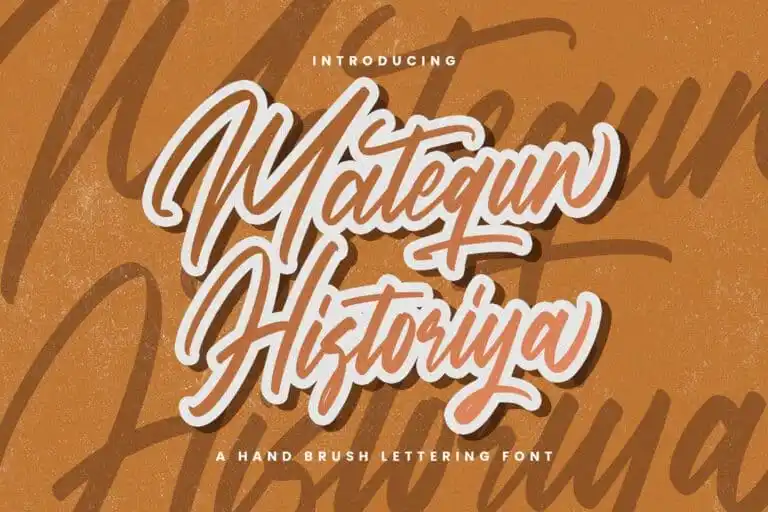
Matequn Historiya Script Font – Download Grátis
Matequn Historiya Script Font é uma elegante fónta de script círrico projetada pela StringLabs para atender a uma ampla variedade de necessidades, desde logomarcas até trabalhos tipográficos. Seu design sofisticado e equilibrado torna-o perfeito para vários ambientes gráficos, incluindo projetos criativos onde um texto fluido pode realçar sua estética e funcionalidade. Este tipo de fonte é ideal para quem busca uma solução que seja tanto elegante quanto versátil, adaptável a muitas demandas e capaz de transformar ideias em realidade visualmente fascinantes. Se você está procurando por uma fonte círrica com um toque especial e adequada para diversos usos gráficos, Matequn Historiya Script Font pode ser o que seu projeto precisa.